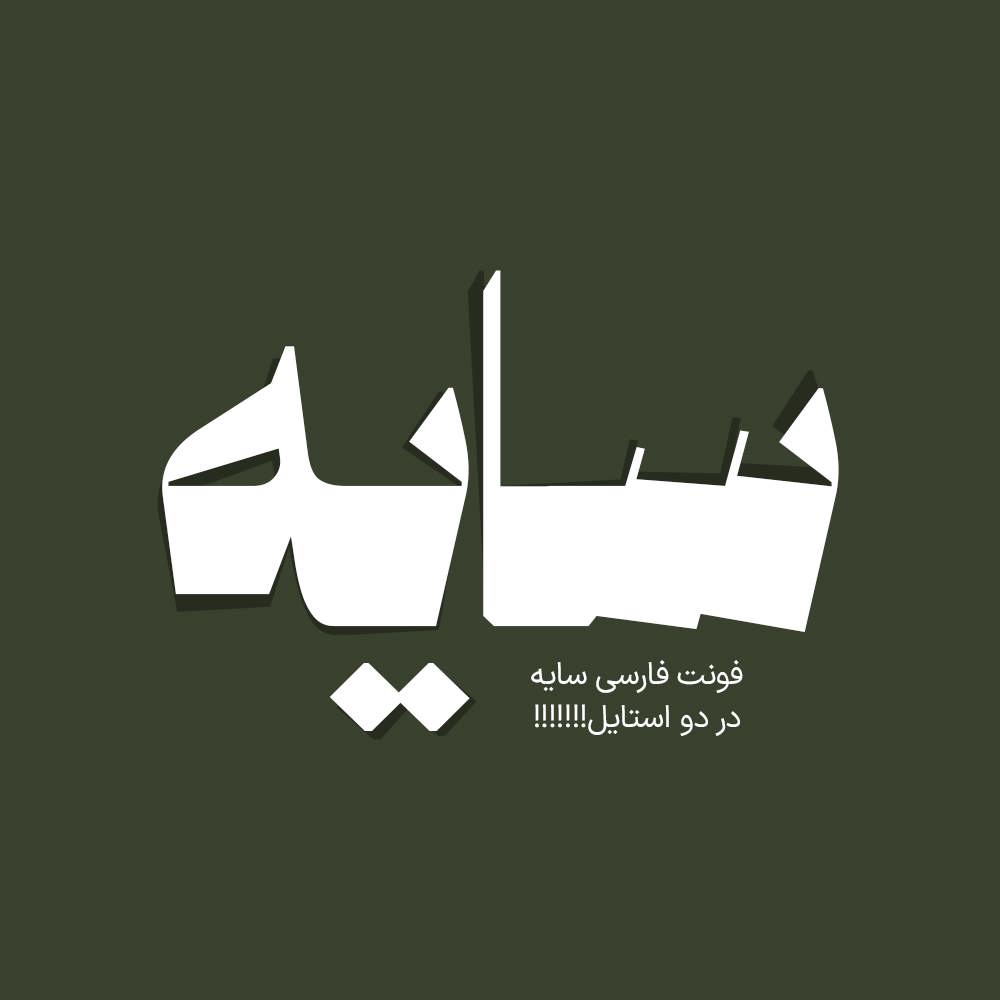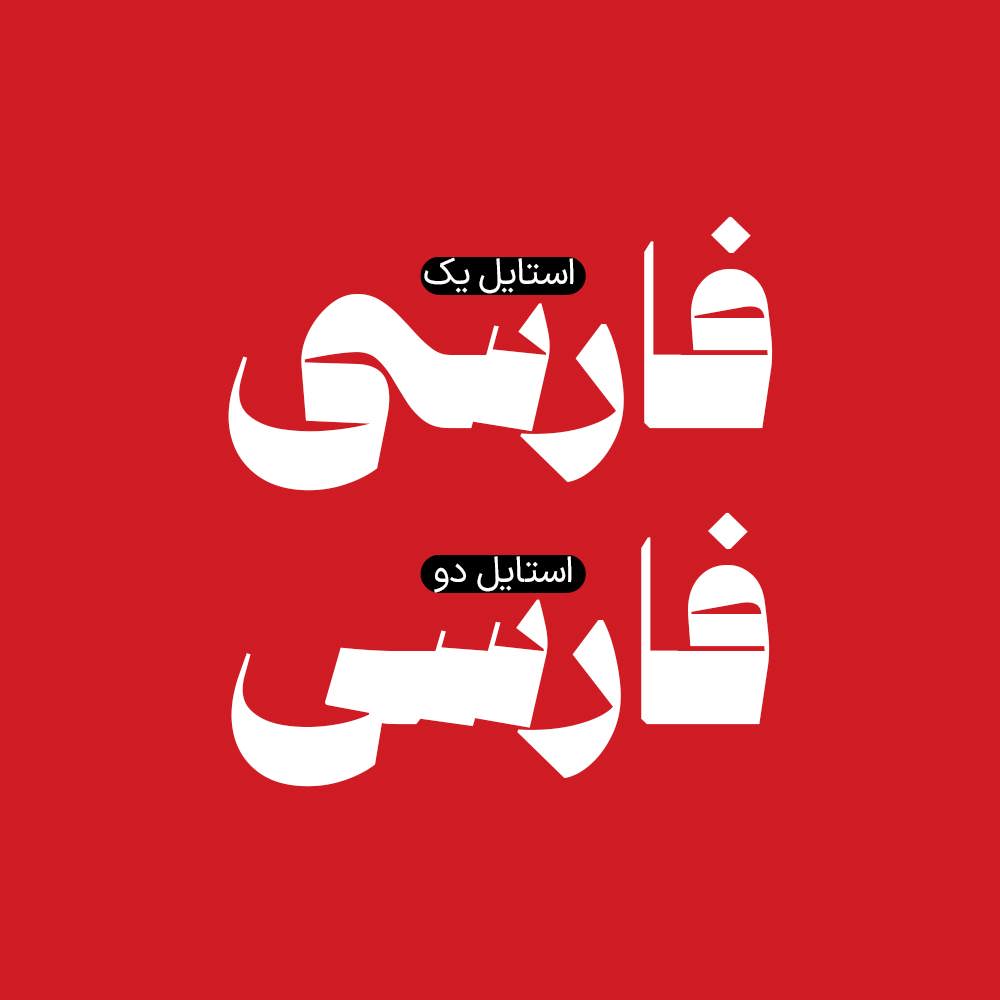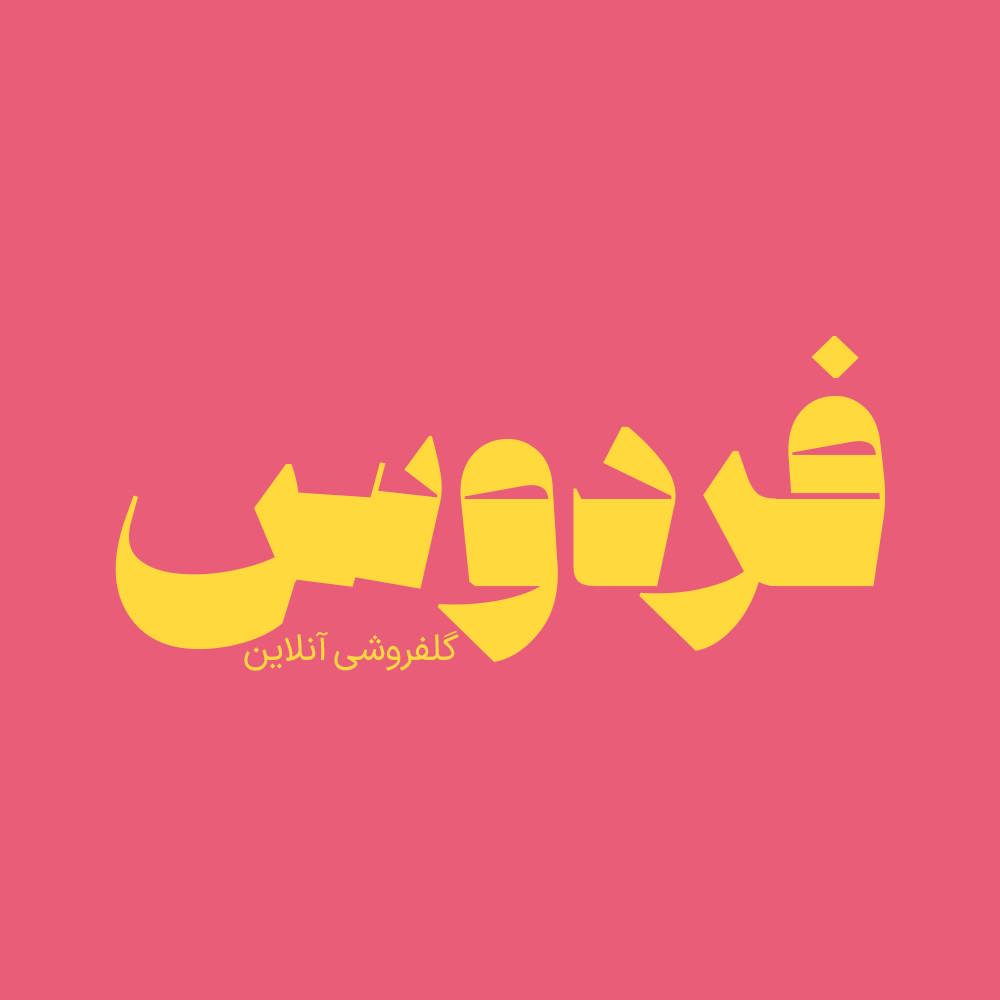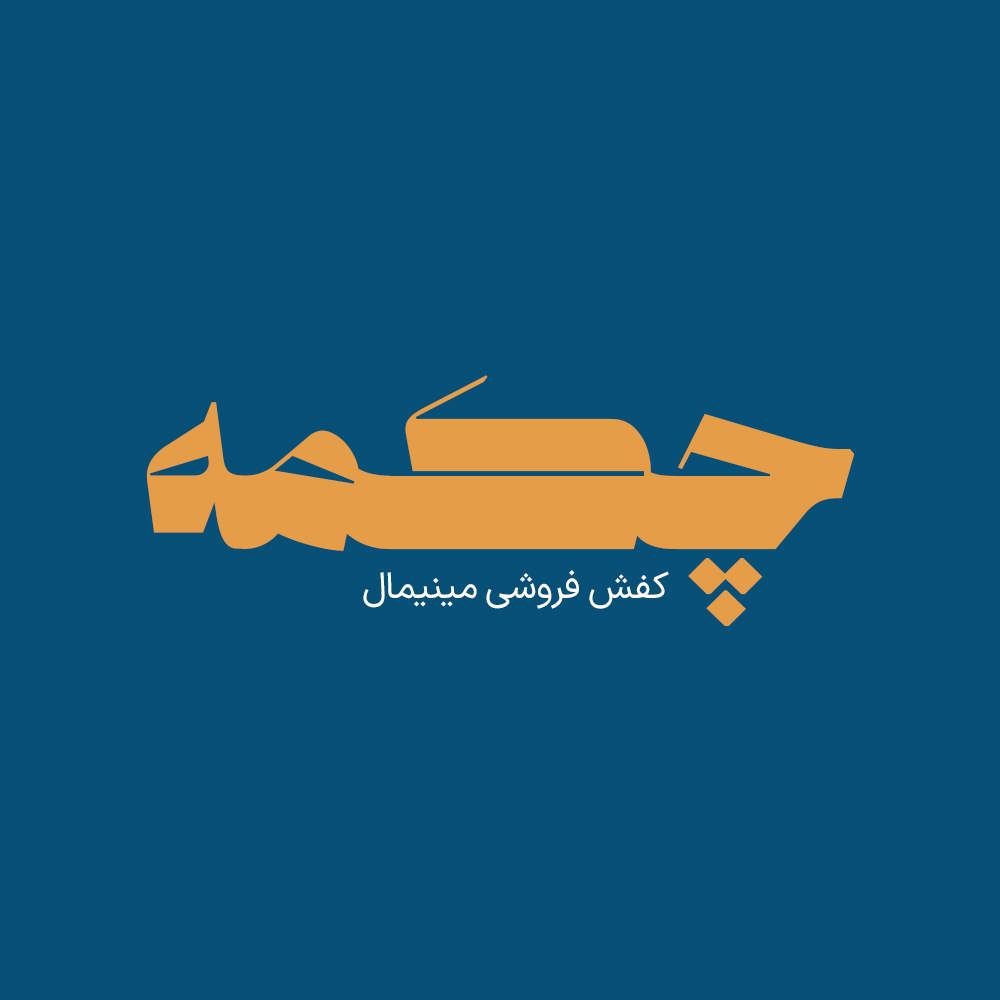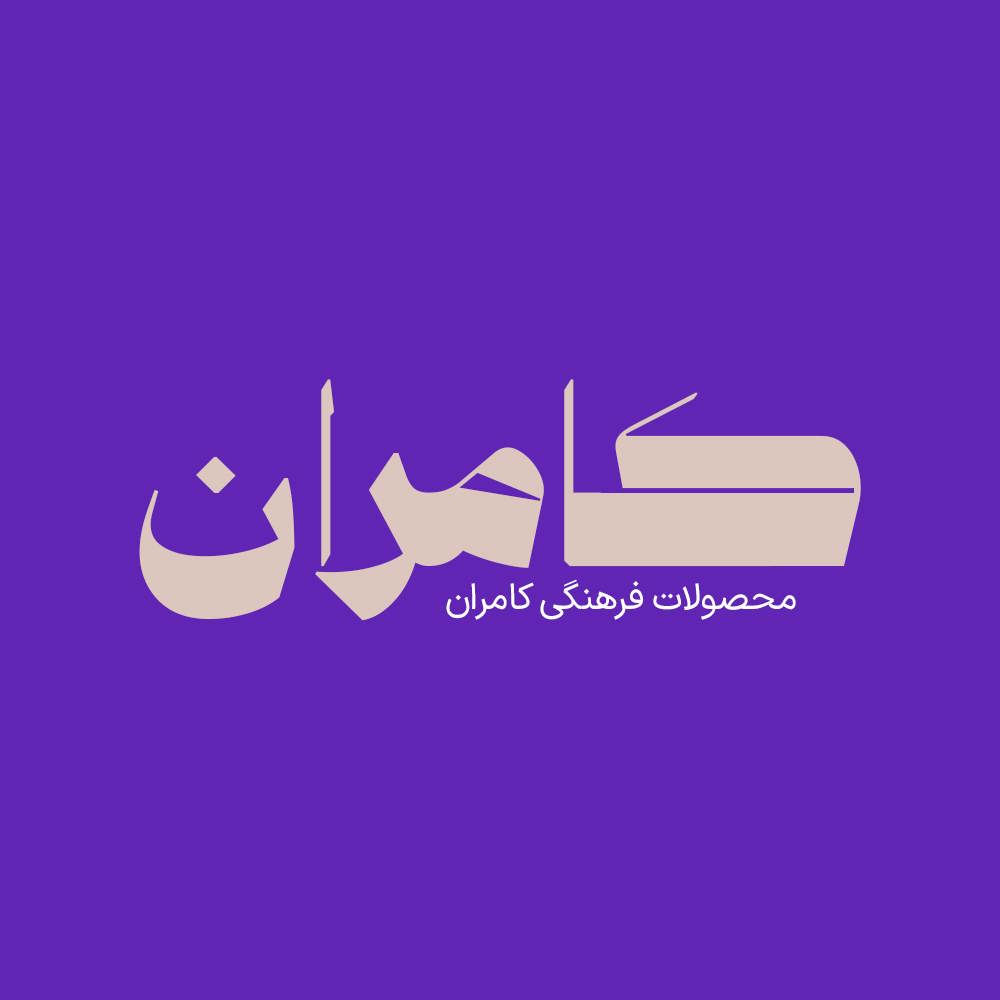
فونت فارسی سایه Sayeh Font
فونت فارسی سایه یک فونت تک وزن با کاربرد طراحی لوگوتایپ و طراحی های مختلف همچون کتاب و تولید محتوای متن های کوتاه و عناوین می…
فونت فارسی سایه یک فونت تک وزن با کاربرد طراحی لوگوتایپ و طراحی های مختلف همچون کتاب و تولید محتوای متن های کوتاه و عناوین می باشد. فونت سایه با ساختار حروف خود مناسب استفاده در لوگوهای نوشتاری می باشد. همچنین از فونت سایه در طراحی تابلوهای چلنیوم هم به دلیل ساختار منحصر به فردش می توانید استفاده کنید. فونت فارسی سایه زیبا و حرفه ای مناسب استفاده در عناوین و تیترها و جملات نسبتا کوتاه و هم طراحی انواع لوگوتایپ، تکست گرافی و استفاده در طراحی های خاص می باشد.
پیشنمایش و نمونه تایپ های فونت سایه